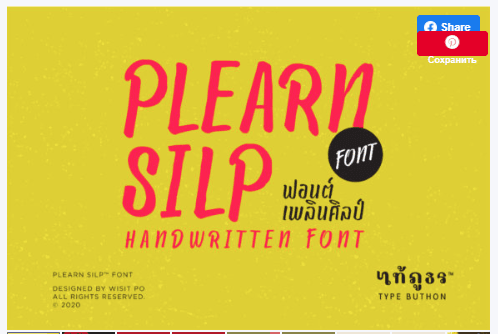
Plearn Silp Font
Plearn Silp - аккуратный, дружелюбный и игривый рукописный шрифт. Независимо от темы, этот шрифт станет невероятным активом в вашей библиотеке шрифтов, так как он может улучшить любое творение.